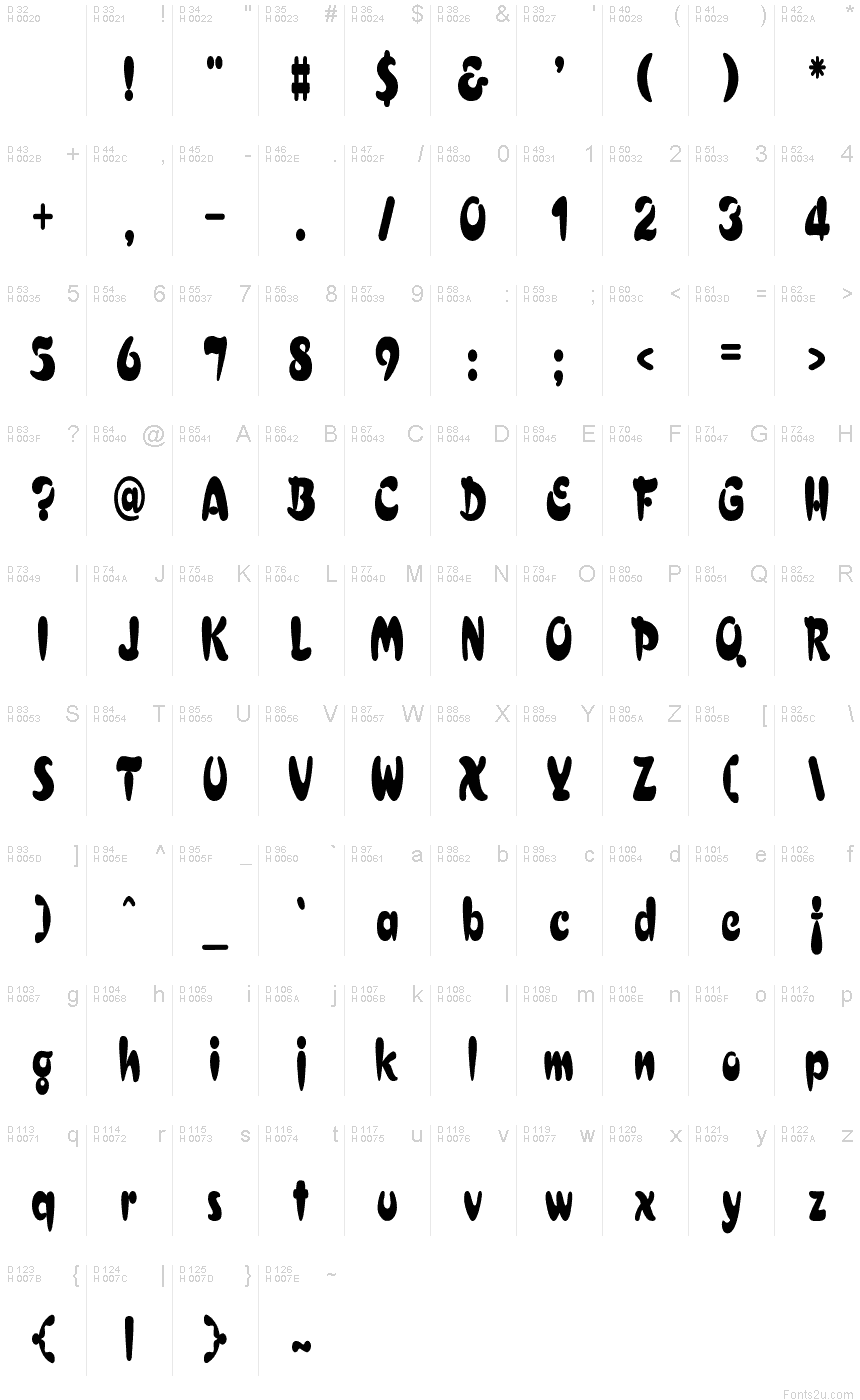
خط Electrik Cn من تصميم A. Carr. هو خط عرض مجاني بنمط القصص المصورة، يتميز بمنحنيات سميكة تشبه الحبر وتجمع في إيحائها بين فقاعة وحركة برق. تضفي ضربات الحروف العالية التي تشبه القطرات والأشكال الانسيابية طابعاً قوياً وشبهاً بالسائل، مما يجذب الانتباه فوراً دون أن يبدو حاداً أو منفراً.
مع Electrik Cn، تبدو العناوين وكأنها انسكبت على الصفحة، مما يجعل هذا الخط المجاني خياراً طبيعياً لملصقات الحفلات، منشورات الفعاليات، المجلات المستقلة، أغطية كتب الأطفال، تغليف الحلويات، وصور مصغرة جذابة على يوتيوب. استخدم الخط بحجم كبير، امنحه مساحة للتنفس، ونسقه مع خط هندسي بسيط بلا زوائد للحفاظ على لمسة عفوية جذابة بعيداً عن الفوضى.
Electrik Cn